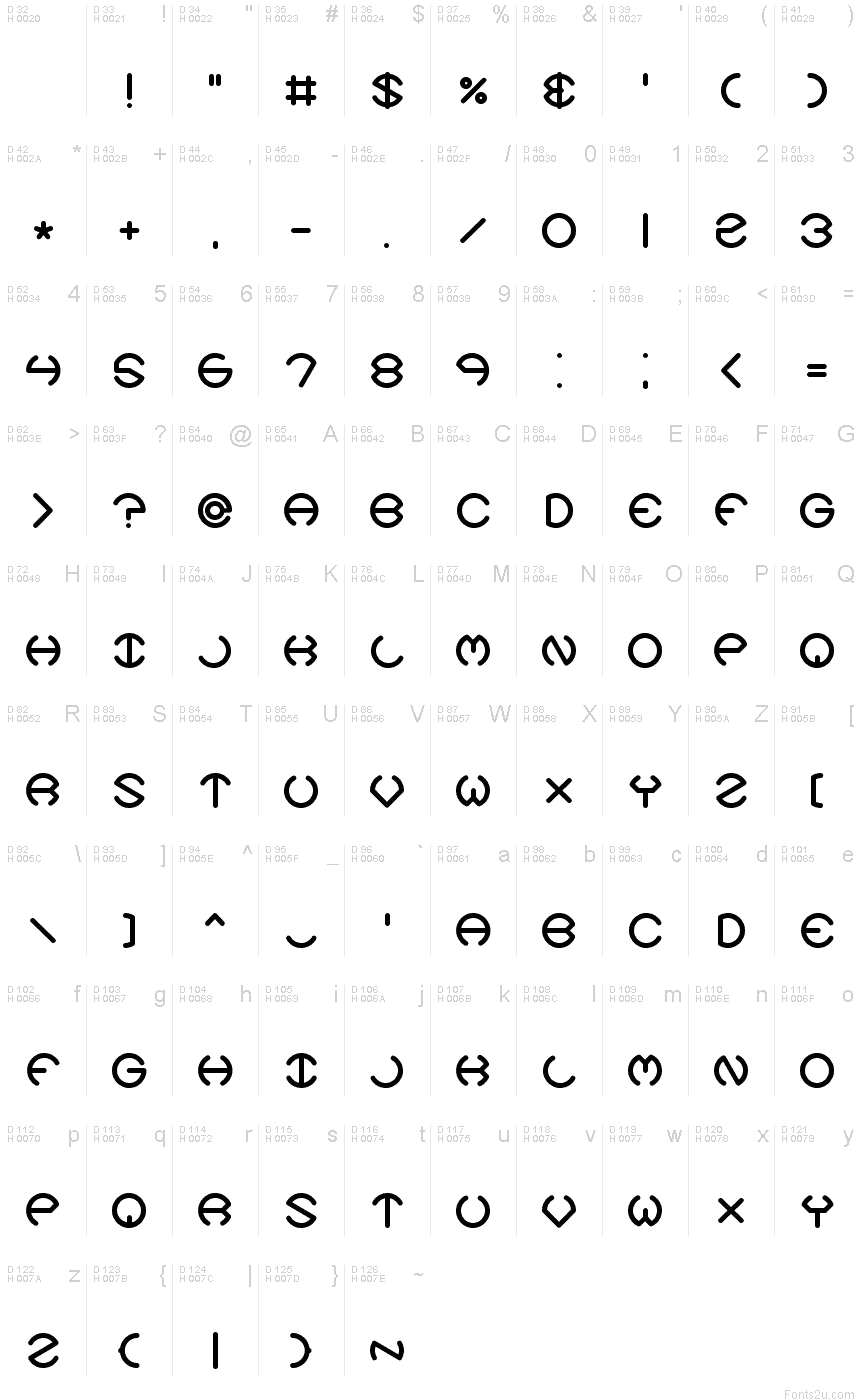
Spheroids X BRK di ÆNIGMA Fonts è un font display futuristico gratuito, caratterizzato da lettere orbitali arrotondate che sembrano scolpite in cerchi e interrotte da netti tagli orizzontali. Il gioco di archi aperti, forme quasi geometriche e spaziature pulite gli conferisce un'eleganza retro-spaziale, che richiama più la segnaletica sci-fi che la comune tipografia decorativa.
Si presta perfettamente a poster, loghi di videogame, artwork musicali, flyer tecnologici e titoli, dove un font gratuito deve trasmettere immediatamente un forte richiamo all'era spaziale. È ideale per titoli brevi, copertine o iniziali, poiché le lettere mantengono intatta la loro personalità grazie a queste forme circolari sezionate, anche in contesti molto brevi.
Spheroids X BRK — Presentazione del carattere